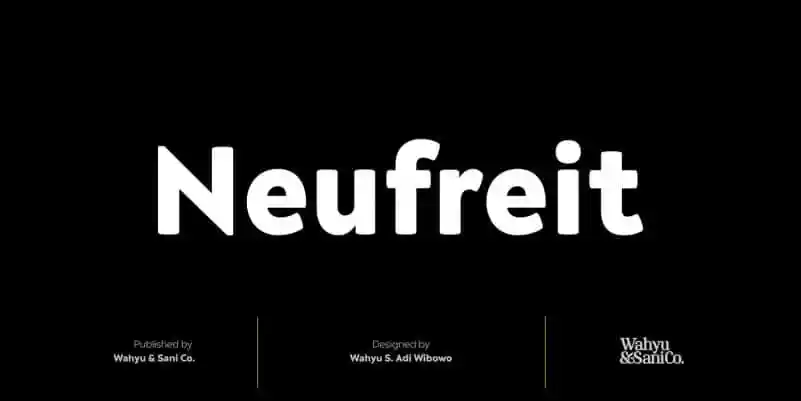
Neufreit Sans Serif é uma obra-prima criada por Wahyu & Sani Co, com um processo rigoroso e extenso que resultou numa fonte séria com 9 pesos diferentes e estilos itálicos correspondentes, desde ExtraLight até ao peso mais pesado conhecido como Heavy. Esta fonte atinge o seu ponto alto na versatilidade e facilidade de leitura, ideal para criar design gráfico em estilo contemporâneo e minimalista. Com um tamanho reduzido e linhas retas que se assemelham a uma linha reta, Neufreit é perfeita para aplicativos digitais que precisam de legibilidade e estética moderna. Seja para editoriais online, design gráfico ou até mesmo para criação de logotipos, Neufreit Sans Serif oferece um design único e de alta qualidade, permitindo a criação de textos com aparência limpa e elegante que se destacará em qualquer projeto.